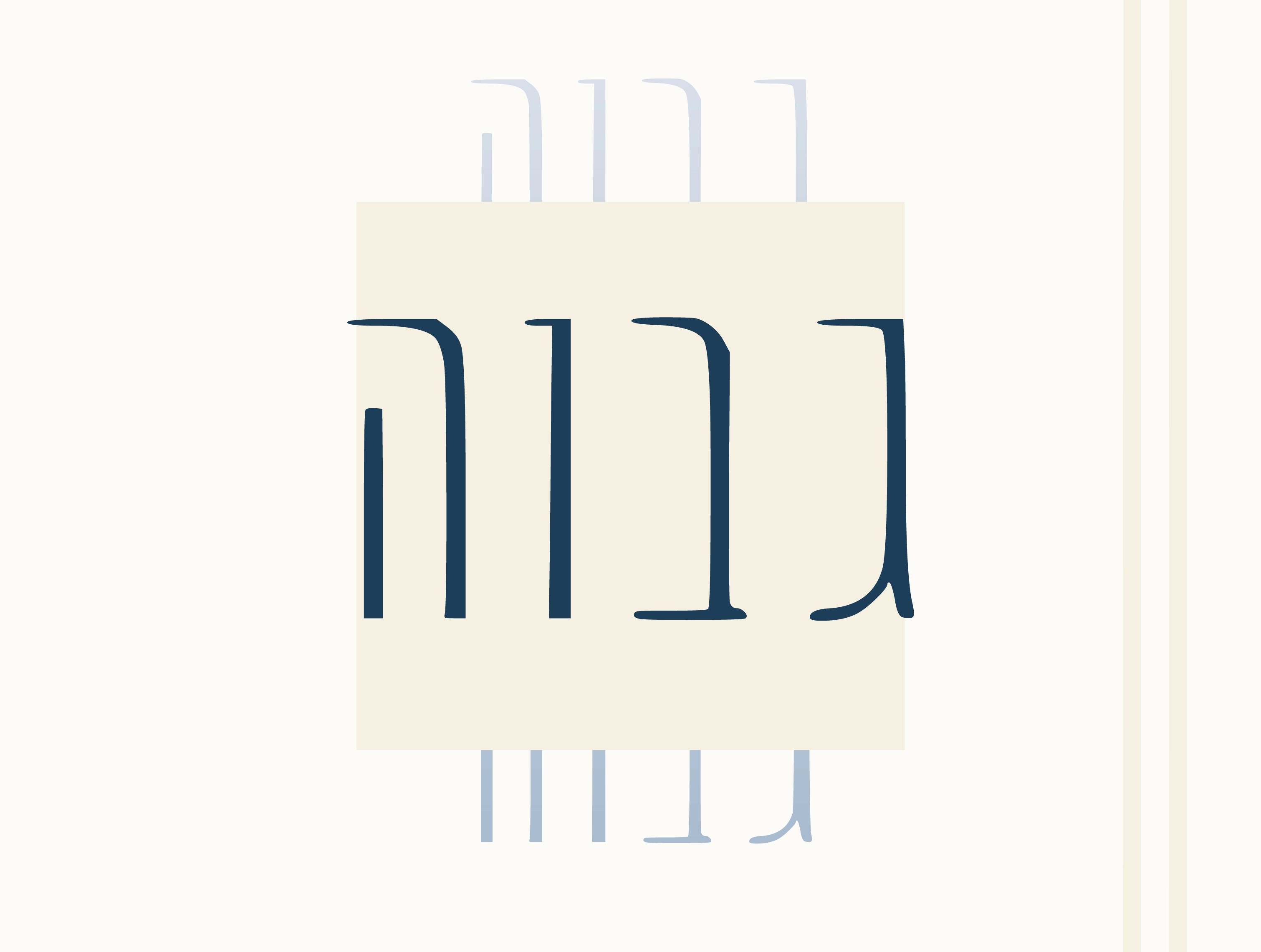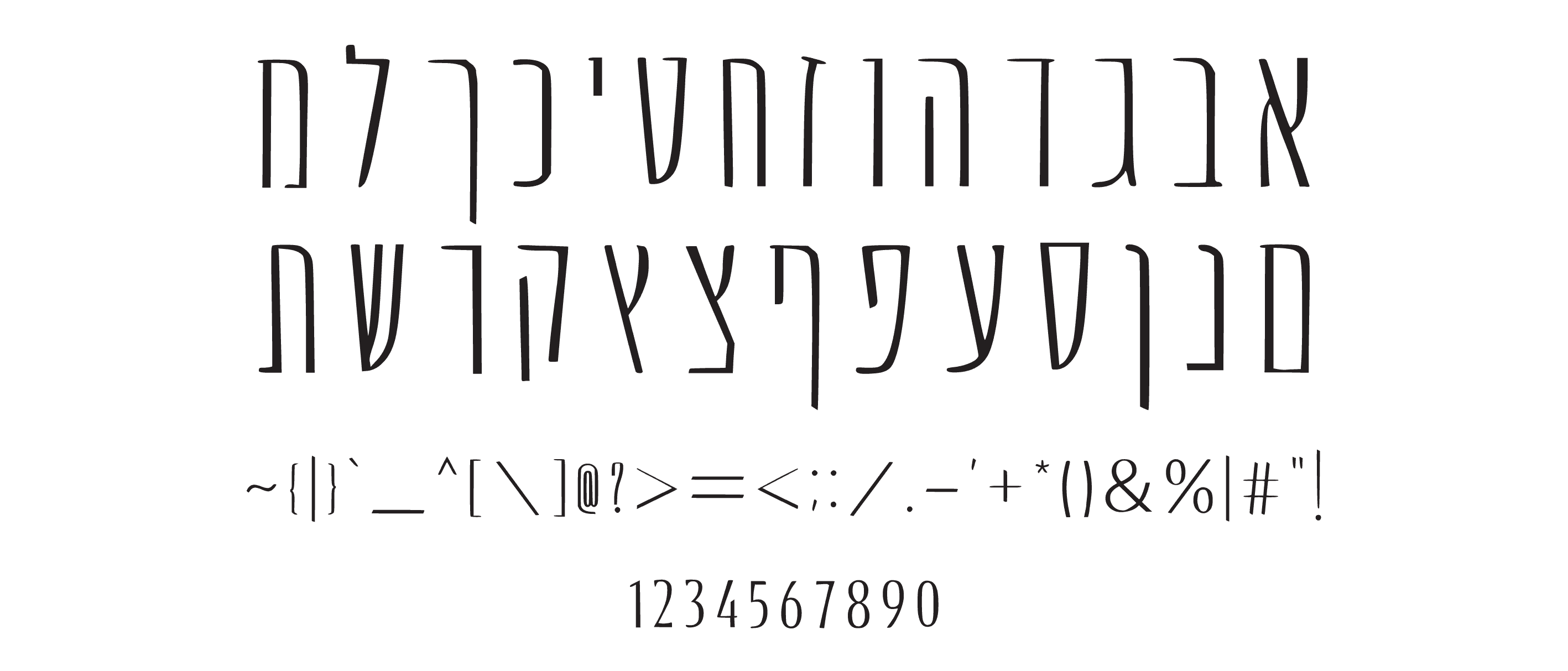
פונט גבוה
Minimalistic and tall Hebrew font, for a particularly elegant and clean appearance.
גבוה — פונט שלא מתפשר
גבוה הוא לא עוד פונט, הוא הצהרת כוונות.
אותיות צרות, אלגנטיות ומוארכות, שמהדהדות גובה, אווריריות וקלאסיקה מודרנית.
הפונט הזה בנוי לאנשים שמבינים עיצוב ורוצים להרים את המיתוג שלהם לגובה אחר.
מה מיוחד בו?
מינימליסטי ונקי, בלי רעש מיותר
שומר על אווירה קלילה, אך עדיין מלא נוכחות
קווים דקיקים ומדויקים שמרגישים כמעט כמו טיפוגרפיה יפנית
איפה הוא מרגיש בבית?
🏷️ מיתוג למותגי יוקרה
🍷 תפריטים של מסעדות עילית
🪞 עיצוב פנים, אדריכלות ואופנה
🎨 מגזינים ומדיה דיגיטלית בעולמות עיצוב
למי הוא מתאים?
למי שמחפש פונט אחר — מיוחד, מינימליסטי, גבוה ואווירירי, כזה שמייצר רושם מיידי של סטייל וניקיון.
זה הזמן להוסיף לו את הקסם שלך.